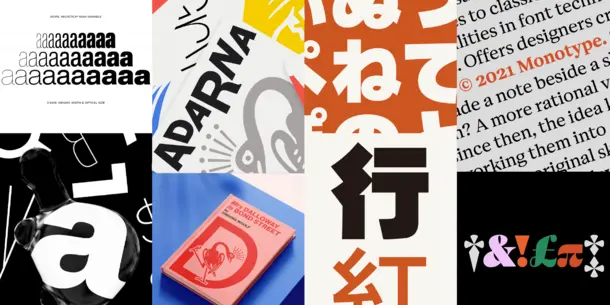
Monotype freut sich über gleich mehrere Awards renommierter Design- und Kreativorganisationen
Designer und Schriften der bekannten Foundry Monotype erhalten Awards von Fast Company, Design & Art Direction, Red Dot und Communication Arts.
Woburn, Mass./ Berlin, 15. Dezember 2022 – Die Experten für Schrift und -Technologie von Monotype freuen sich über gleich mehrere Auszeichnungen und Anerkennungen: über den Innovation by Design Award von Fast Company, den Wood Pencil von Design & Art Direction (D&AD), den Red Dot Design Award und über den Typografie-Wettbewerb von Communication Arts für die Jahre 2022 und 2023. Die Auszeichnungen stehen stellvertretend für die Vielfalt der Schriftkollektionen von Monotype, die von einigen der besten Schriftdesigner der Welt entwickelt wurden, und unterstreichen die globale Reichweite, mit der das Unternehmen Kreativen seine Produkte und Dienstleistungen anbietet.
„Schrift ist ein wesentlicher Bestandteil von Markenidentitäten. Wir hoffen, dass diese Auszeichnungen dazu dienen, diesen Aspekt noch stärker zu beleuchten und insgesamt mehr kreative Augen auf unsere Schriften lenken werden,“ sagt Charles Nix, Executive Creative Director bei Monotype. „Wir freuen uns sehr, dass unsere Arbeit auf globaler Ebene anerkannt wird.“
Die Awards im Einzelnen
1. Fast Company’s Innovation by Design Awards 2022
Monotype ist Finalist bei den Fast Company’s 2022 Innovation by Design Awards in der Kategorie Grafikdesign für das Typografie-Projekt „Helvetica Goes Variable: 1 Million New Styles“.
Helvetica Now Variable bietet mehr als 1 Mio. neue Helvetica-Stile in einer hochmodernen Schriftdatei. Diese ermöglicht es Designern, Marken und Verbrauchern, unendliche Ausdrucksschattierungen, typografische Animationen und damit raffinierte Typografien zu schaffen. Helvetica Now Variable ist nicht nur eine Fortsetzung der aus dem Jahr 2019 stammenden Version von Helvetica Now - sie eröffnet neue typografische Ausdrucksmöglichkeiten mit ungeahnter Tiefe, Dimension und Möglichkeit.
„Ein gemeinsames Thema der diesjährigen Innovation by Design-Preisträger, die von Schnittstellen im Gesundheitswesen bis hin zu Technologien für autonomes Fahren reichen, ist Beständigkeit“, so Brendan Vaughan, Chefredakteur von Fast Company. „Die Produkte, die unseren Redakteuren und Juroren ins Auge sprangen, widersprechen unserer schnelllebigen Konsumkultur, während sie gleichzeitig eine umfassendere Vision von Design verkörpern.“
Die Innovation by Design Awards wurden in diesem Jahr zum insgesamt 11. Mal verliehen und zeichnen eine Reihe von Blue-Chip-Unternehmen, aufstrebenden Startups und jungen Talenten aus. Der Preis gehört zu den begehrtesten der Branche.
2. D&AD Wood Pencil 2022
Den D&AD Wood Pencil erhält Monotype gemeinsam mit Nike für 耐克365 / Nike365 – die erste chinesische typografische Identität von Nike – die vom Nike Shanghai Studio und Monotype entworfen wurde. Der Preis zeichnet die besten Arbeiten des Jahres in den Bereichen Werbung, Design, Handwerk, Kultur und Einfluss aus.
Die Schrift umfasst 8.503 chinesische Schriftzeichen, die sich durch ihre extreme Schwere und den verdichteten Schriftsatz auszeichnen – zwei ungewöhnliche und schwierige Merkmale für die komplexe chinesische Schriftsprache.
Die D&AD Pencils werden seit 1962 den Besten der Besten in Design und Werbung verliehen. Der weltweit anerkannte Preis ist die ultimativ kreative Auszeichnung und ein Höhepunkt vieler Karrieren. Denn die Arbeiten inspirieren Andere dazu, sie zu studieren, zu diskutieren, zu kopieren und auf sie zu referenzieren.
3. Red Dot Design Award 2022
Drei Schriften aus dem Hause Monotype sind mit dem Red Dot Award in der Kategorie Marken- und Kommunikationsdesign ausgezeichnet worden: Helvetica Now Variable, Cotford und Shorai™ Sans. Die Auszeichnung wird von international führenden Köpfen der Branchen vergeben und sind ein weiterer schöner Beweis für die kreative Leistung des Unternehmens.
Der Red Dot Design Award ist einer der größten Designwettbewerbe der Welt und die Auszeichnung „Red Dot“ steht global für herausragende Designqualität.
4. Communication Arts‘ Typografie-Wettbewerb2023
Obwohl Monotype die Schrift Touvlo erst im September dieses Jahres herausbrachte, wurde sie schon jetzt zum Gewinner der 13. jährlichen Communication Arts Typography Competition gekürt. Touvlo ist eine schwungvolle, moderne Interpretation eines klassischen Genres, die den Geist früher britischer Groteskschriften gekonnt einfängt und gleichzeitig eine eigene lebendige Persönlichkeit und Energie zum Ausdruck bringt.
Aus 1.112 eingereichten Beiträgen wählte die Jury 137 Projekte aus, die den besten Einsatz von Typografie, neuen Schriftentwürfen, Kalligrafie und Handlettering hervorheben.
Auch der Communication Arts Award gehört zu den begehrtesten Auszeichnungen der Branche.